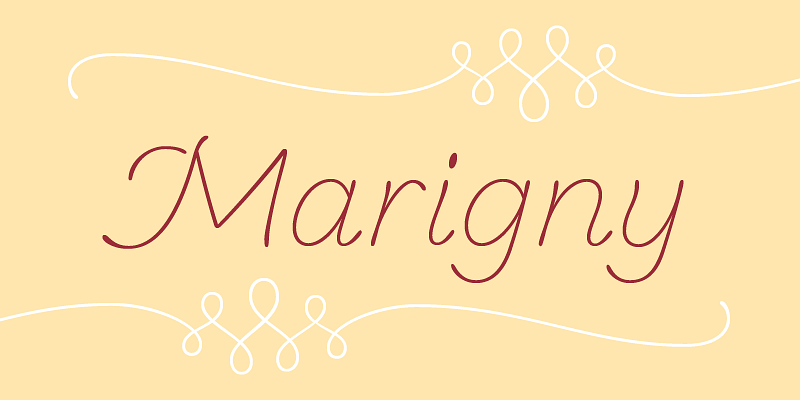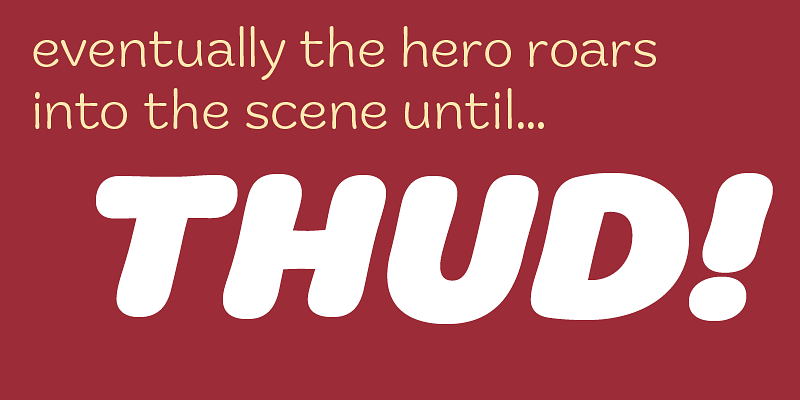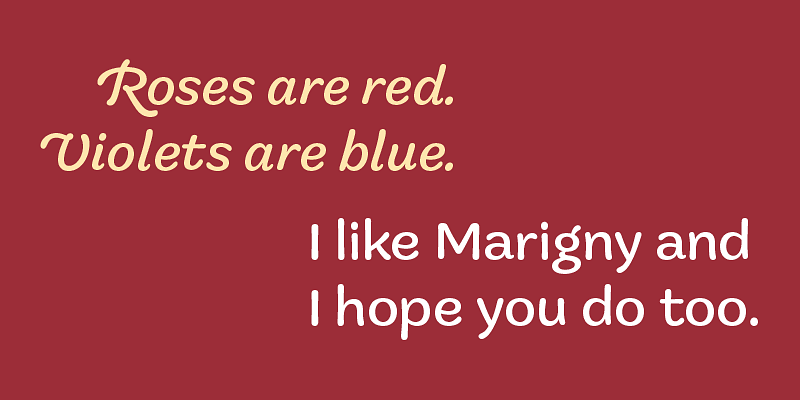
Marigny est une police simple, mais qui prend son rôle très au sérieux. Elle allie le ton chaleureux de l’écriture manuscrite au pragmatisme de la composition pour offrir des blocs de texte, des titres immenses, et toutes sortes de présentations engageantes.